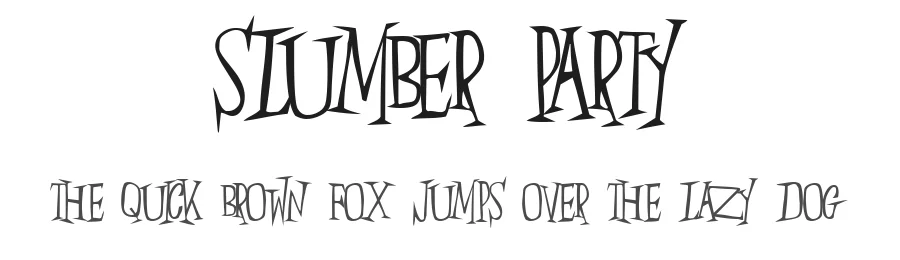
About Surabanglus Font
Surabanglus diambil dari judul salah satu cerita pendek Ahmad Tohari dalam bukunya "Senyum Karyamin". Surabanglus sendiri adalah nama dari sejenis ketela yang beracun jika dimakan.
Surabanglus Font is a decorative font that shines as a display or heading face. Pair it with a clean sans-serif or serif font for body text β the contrast creates a clear hierarchy while the two styles stay balanced and easy to read.